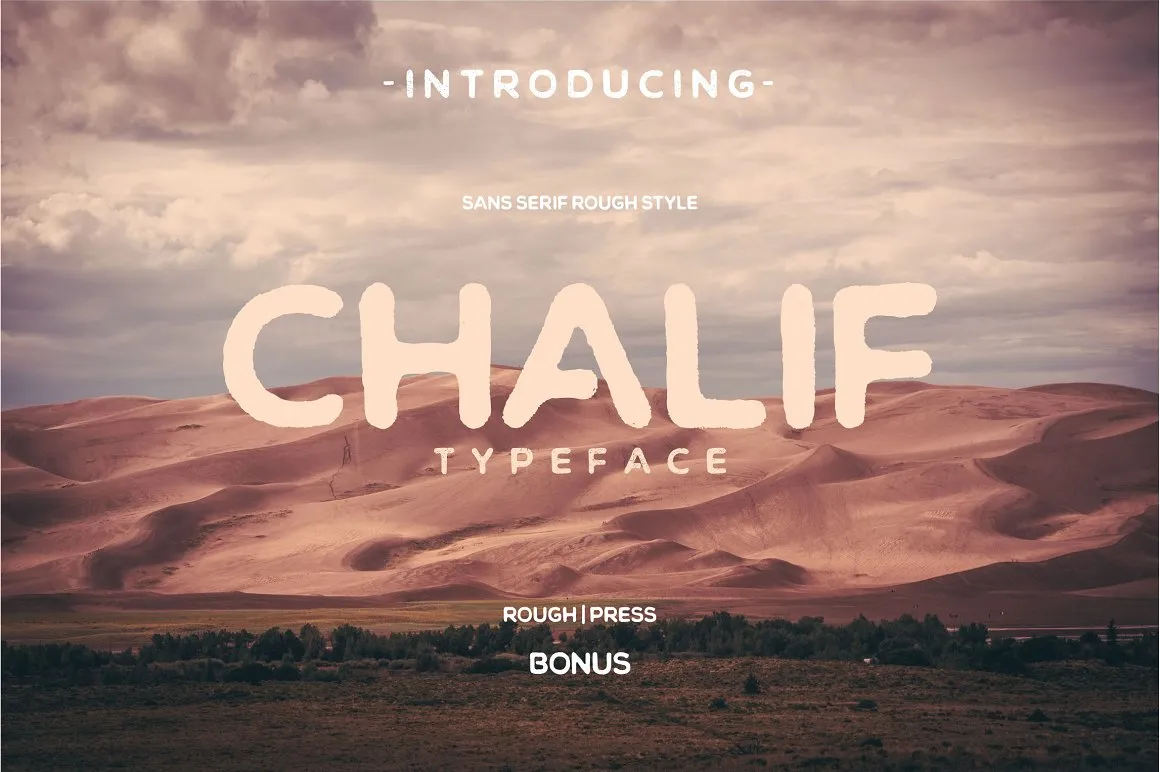
A Chalif Typeface é uma fonte de estilo Display que foi criada pelo designer independente 178-MC. Esta fonte está disponível para download gratuito no CreativeMarket, um marketplace popular para designers e profissionais de marketing visual. A Chalif Typefaces tem um design sans serif, mas incorpora elementos de desenho a mão em seu estilo, oferecendo duas opções alternativas: uma versão “rough” mais suave e outra que se aproxima mais da aparência de desenhos manuais. Ela é ideal para projetos de moda, logomarcas vintage, rótulos, posteres e embalagens, proporcionando aos designers a oportunidade de criar designs únicos e autênticos. Além disso, inclui um bônus com um logo em desenho à mão, uma excelente adição para qualquer projeto que exige elementos gráficos interessantes e diferentes. A Chalif Typeface é perfeita para qualquer designer buscando incorporar um toque único e autêntico a seus projetos de design visual.